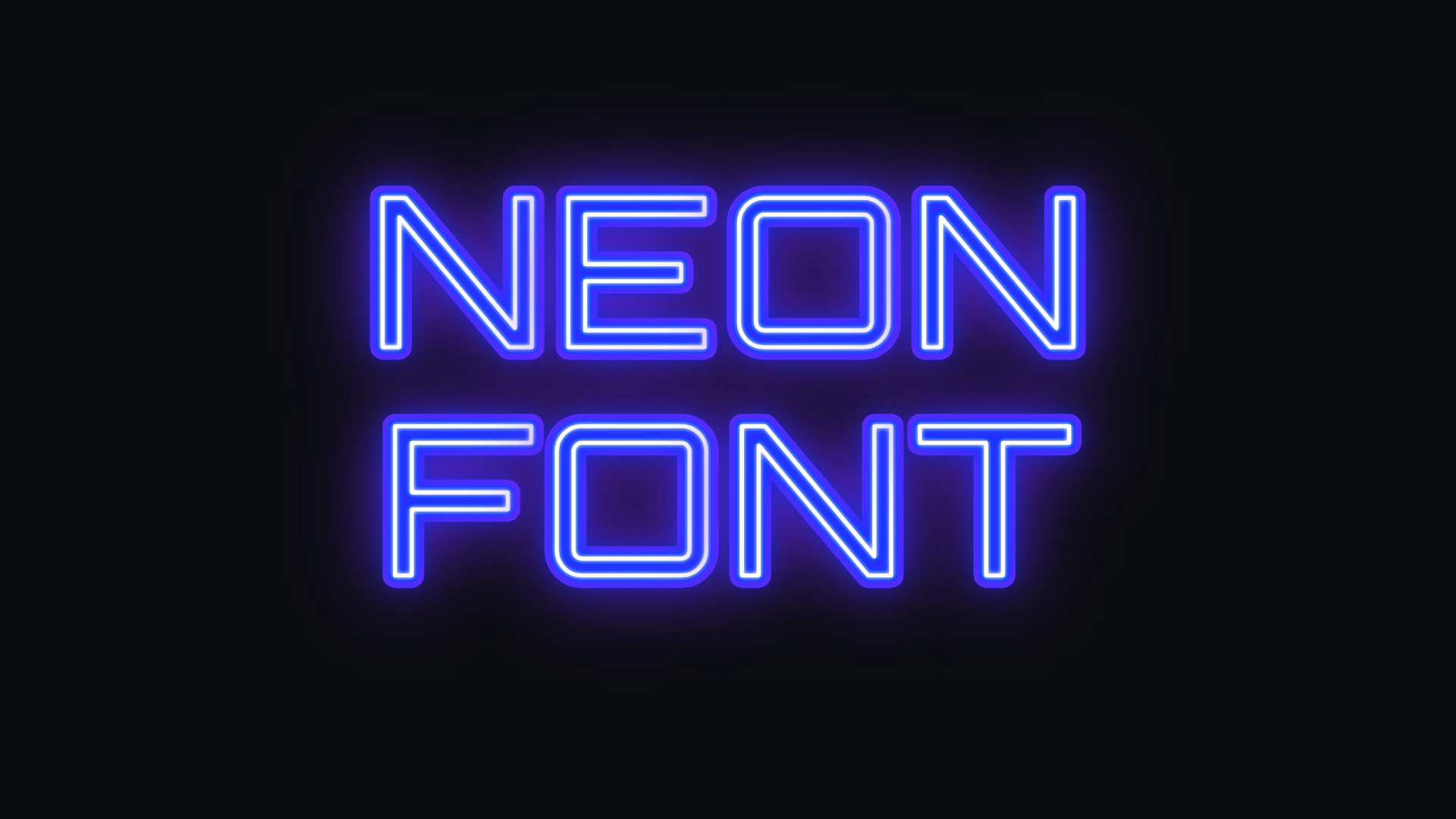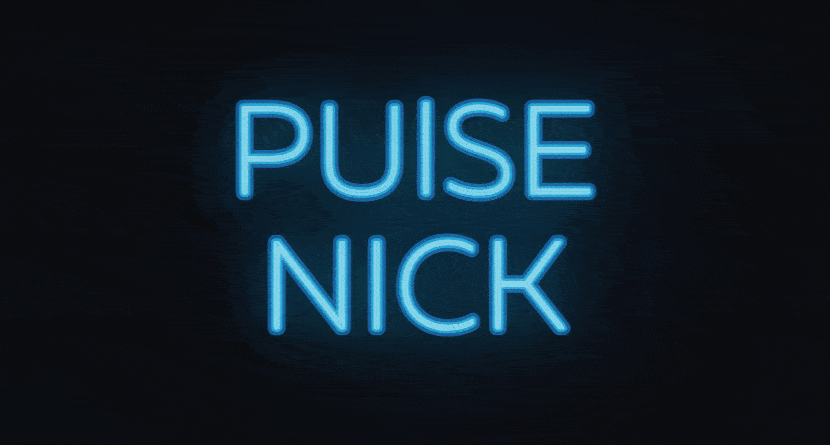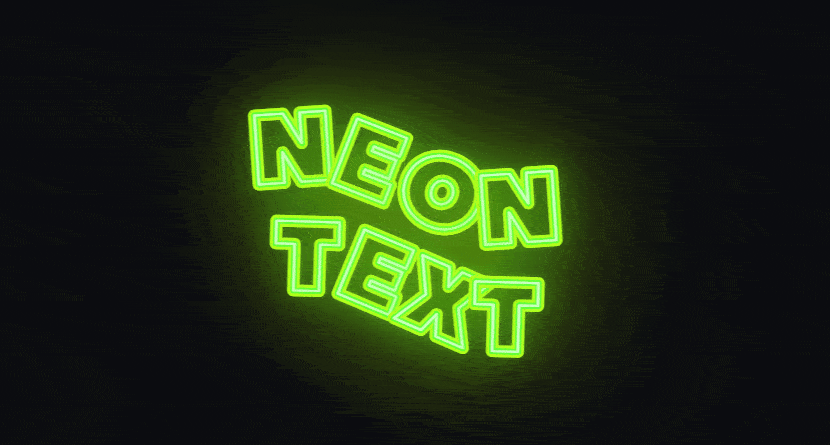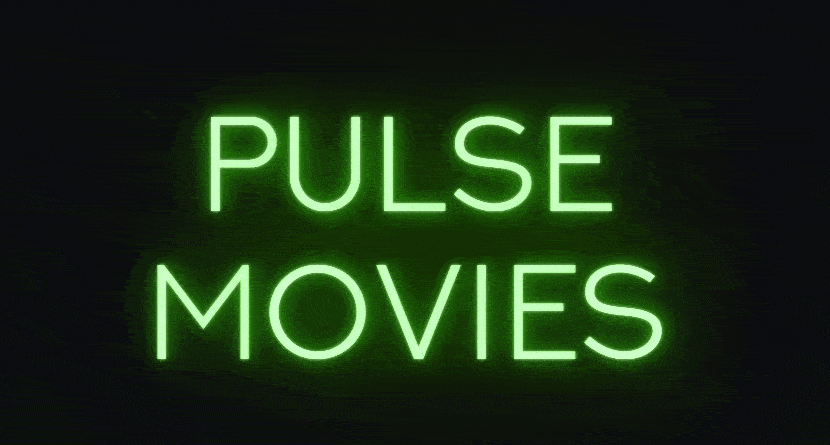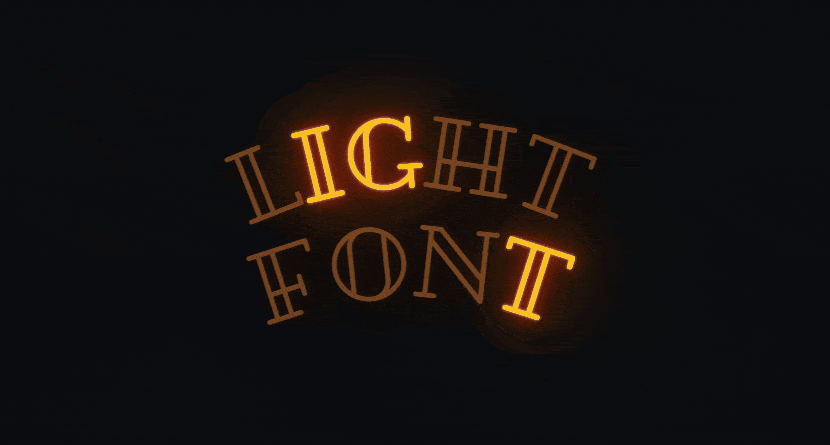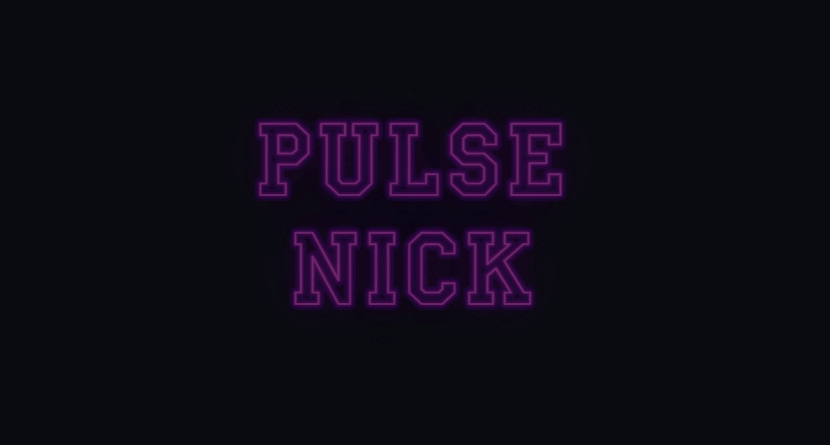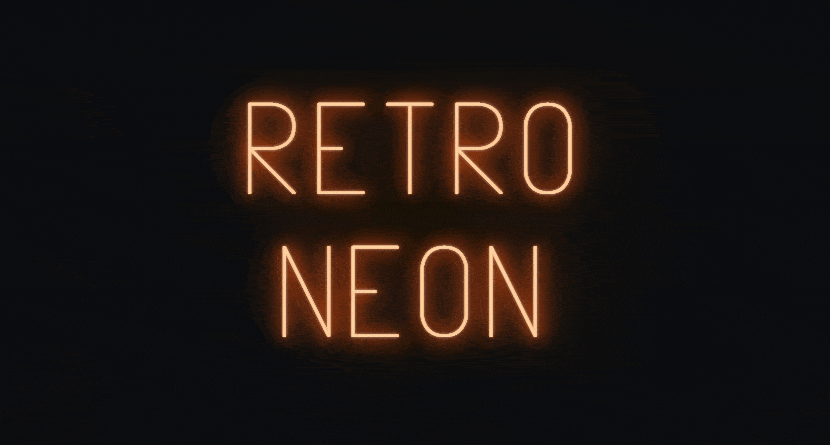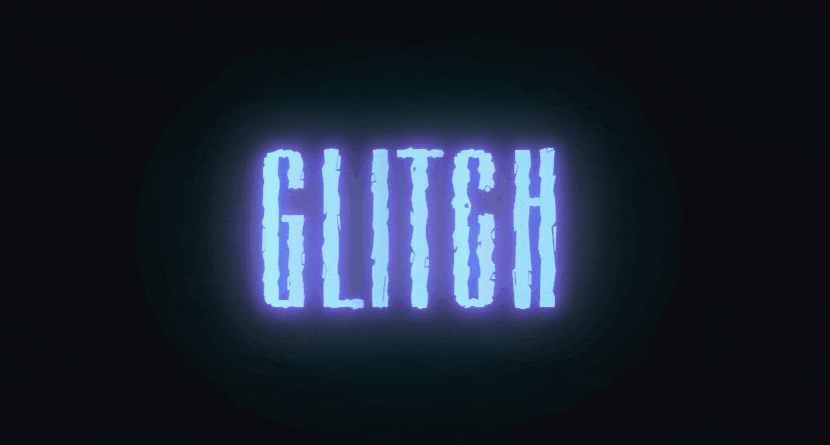
Создай красивую надпись или светящийся ник неоновым шрифтом
Мечтаешь о ярком неоновом никнеме для стрима или просто о красивой надписи для сторис? Наш генератор превратит твой текст в эффектный неоновый шрифт. Это бесплатно и занимает пару секунд.
Галерея красивых шрифтов и неоновых эффектов
Выбери стиль для своего светящегося ника. От классического неона до динамичной анимации — твой никнейм запомнят!
Один из наших красивых шрифтов (рукописные, гранжевые, строгие) и настрой цвет свечения. Сделай ник неоновым шрифтом своей мечты.
Секрет в сочетании: возьми плавный рукописный шрифт (например, Pacifico), выбери яркий насыщенный цвет (розовый, голубой, зеленый) и добавь среднюю интенсивность свечения. Это создаст эффект настоящей неоновой трубки для твоего ника.
О генераторе неоновых ников
Neon Text FX — это твой личный инструмент для создания ярких неоновых надписей и крутых светящихся ников. Мы собрали лучшие красивые шрифты и добавили к ним реалистичные эффекты неона. Забудь про скучные буквы — выделяйся с помощью нашего генератора! Сделай ник неоновым шрифтом и привлекай внимание зрителей и подписчиков.